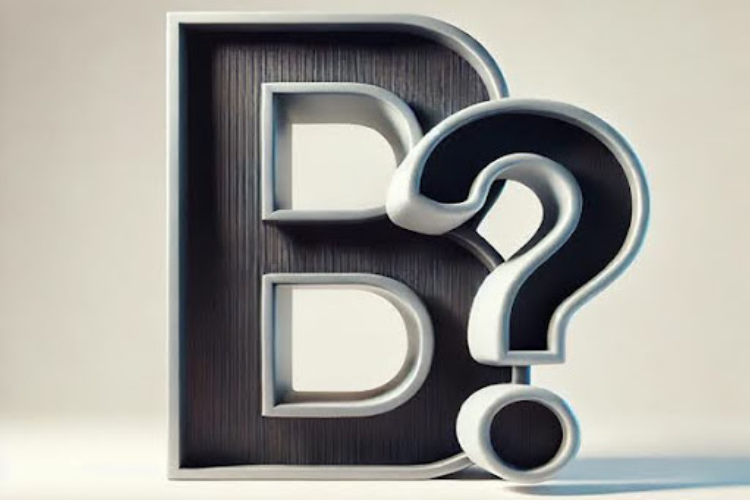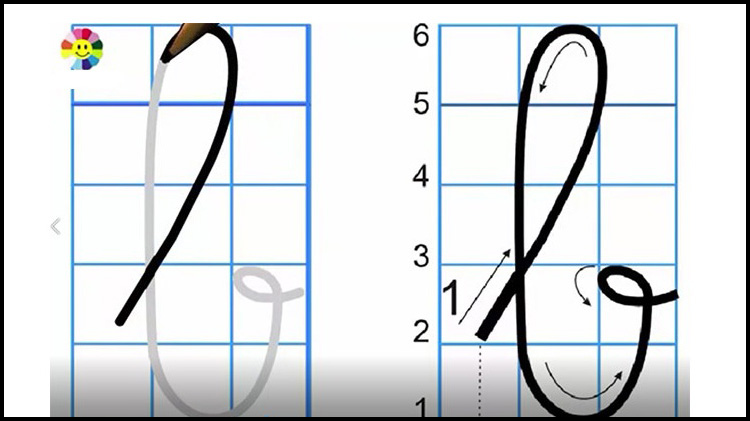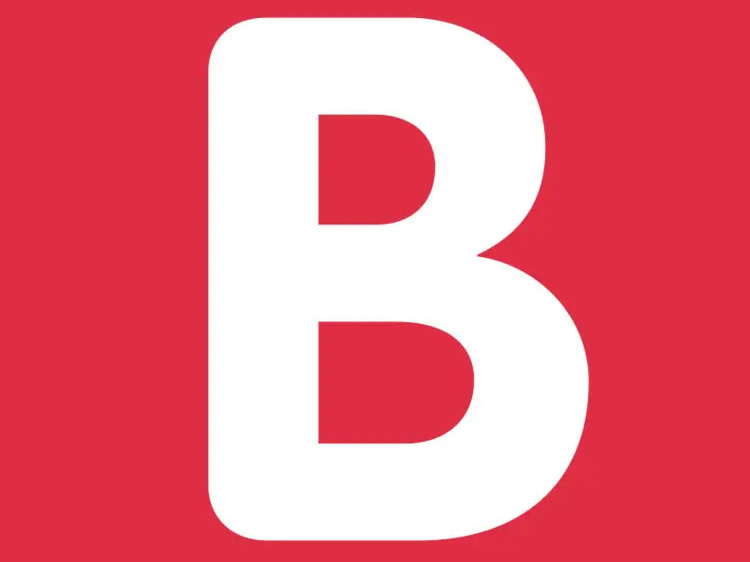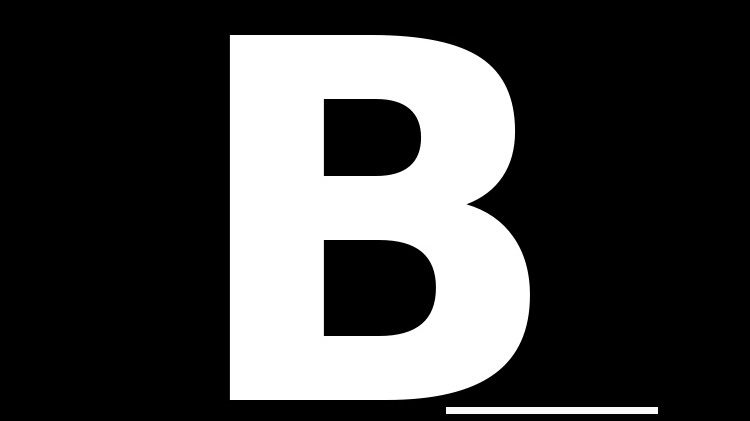
Bộ kí tự đặc biệt chữ B viết thường, in hoa, ngược, cách điệu đầy ấn tượng
Kí tự đặc biệt chữ B được biết đến là các biến thể độc đáo, trang trí, hoặc khác chuẩn của chữ cái B trong hệ thống Unicode. Khi sử dụng những kí tự đặc biệt này không chỉ giúp tên gọi, nickname hay câu khẩu hiệu của bạn trở nên độc đáo mà còn thể hiện cá tính riêng biệt trên các nền tảng mạng xã hội, game hay blog cá nhân.
Trong bài viết sau của MobiFonts sẽ chia sẻ đến bạn đọc bộ sưu tập những kí tự chữ B viết thường, in hoa, viết ngược, chữ cách điệu, kí tự đặc biệt chữ B trong khung được sử dụng trên các nền tảng số hiện nay. Hãy cùng chúng tôi khám phá những kí tự đặc biệt B bắt mắt này để tăng sự thu hút của tất cả mọi người nhé!
Kí tự đặc biệt chữ B viết thường là các ký tự trong hệ thống Unicode có hình dáng giống hoặc gần giống với chữ cái Latin thường "b", nhưng mang kiểu dáng biến thể, trang trí, biểu tượng, hoặc từ hệ chữ khác.
Dạng kí tự này thường được dùng để trang trí văn bản nghệ thuật, đặt tên người dùng, nickname dễ thương như 𝓫𝓸𝔂_𝕓𝓪𝓭, 𝒃𝓮 𝔂𝓸𝓾𝓻𝓼𝓮𝓵𝓯,...
Tham khảo ngay những kí tự chữ B viết thường đẹp, sáng tạo nhất trong bảng sau đây:
Tương tự chữ cái viết thường thì kí tự đặc biệt chữ B in hoa cũng là các dạng biến thể phong cách hoặc ký hiệu biểu tượng, chúng thường có hình dáng thu hút, sáng tạo hoặc mang ý nghĩa đặc biệt — dùng để tăng tính thẩm mỹ, cá nhân hóa, hoặc biểu tượng hóa trong văn bản số.
Sau đây là bảng tổng hợp một số chữ B hoa kiểu nổi bật và độc đáo được yêu thích nhất hiện nay:
Kí tự chữ B ngược là nhóm các kí tự dạng phản chiếu, đảo ngược hoặc tương tự chữ cái B lật ngược. Những kí tự này thường có hình dáng giống chữ b, d, q, B ngược hoặc thuộc các hệ chữ cổ, ký hiệu ngôn ngữ bản địa hoặc hệ ngữ hiếm (Lycian, Deseret, Lisu, Yi…).
Chúng thường được dùng để gây ấn tượng, tạo các hiệu ứng lạ mắt, mã hóa văn bản, thiết kế nghệ thuật trên mạng xã hội và trong game như:
ᑫɒp ʎoԍ
ǝʌɐɹq ǝq
ǝqɐq
ᙠIG ᙠOY
ᙠAD ᙠOSS
ᙠEAST
Dưới đây là bảng tổng hợp các kí tự đặc biệt chữ B viết ngược theo nhiều phong cách nghệ thuật và font Unicode tương ứng mà bạn có thể sao chép để sử dụng tùy mục đích:
Chữ B kí tự đặc biệt cách điệu đầy nghệ thuật là những biến thể sáng tạo của chữ cái B được thiết kế với kiểu dáng, hoa văn, khung, hoặc phong cách độc đáo khác với chữ B thông thường như ♭, ฿, ß, ꞗ,...
Nhiều ký tự trong danh sách này có thể không phải là chữ cái B, nhưng có hình dáng gần giống hoặc cách điệu từ chữ B, nên rất hữu ích cho việc tạo tên nhân vật độc lạ, mã hóa hoặc trang trí văn bản kiểu nghệ thuật.
Sau đây là một số kí tự chữ B đặc biệt cách điệu đẹp được nhiều người yêu thích. Bạn có thể dễ dàng copy và sử dụng chúng từ bảng sau: